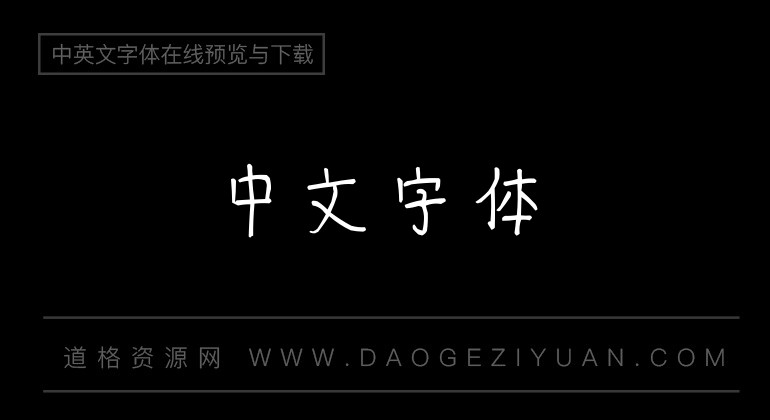
伯乐童年是一款字体,由设计师梁玉芬(Liang Yufen)设计,它是一款简约的楷体字体,设计风格宛如童趣般的温暖,营造出浓浓的童年气息。它的字体线条圆润流畅,结构紧凑简洁,让人一看就有一种温暖的感觉。伯乐童年字体可以用于各种类型的文字、图片、商标等,最适合用于小朋友的书籍、画册、海报等,充满童趣,使文字更加生动有趣。文件名:BoLeTongNianTi-2.ttf
伯乐童年是一款非常不错的手写艺术字体,具有很好的视觉感,适合于文化类的宣传设计、商业类品牌的广告和产品包装设计以及个性化文字排版等较多场景。